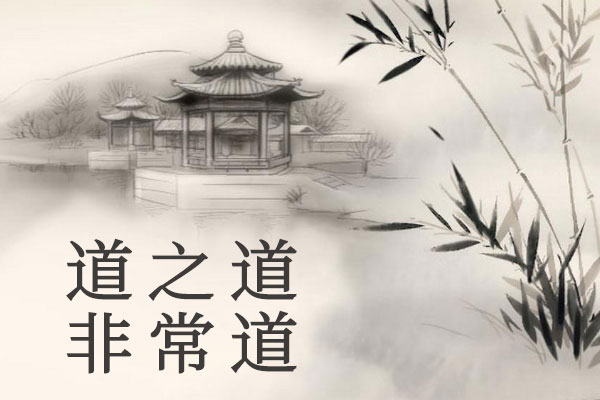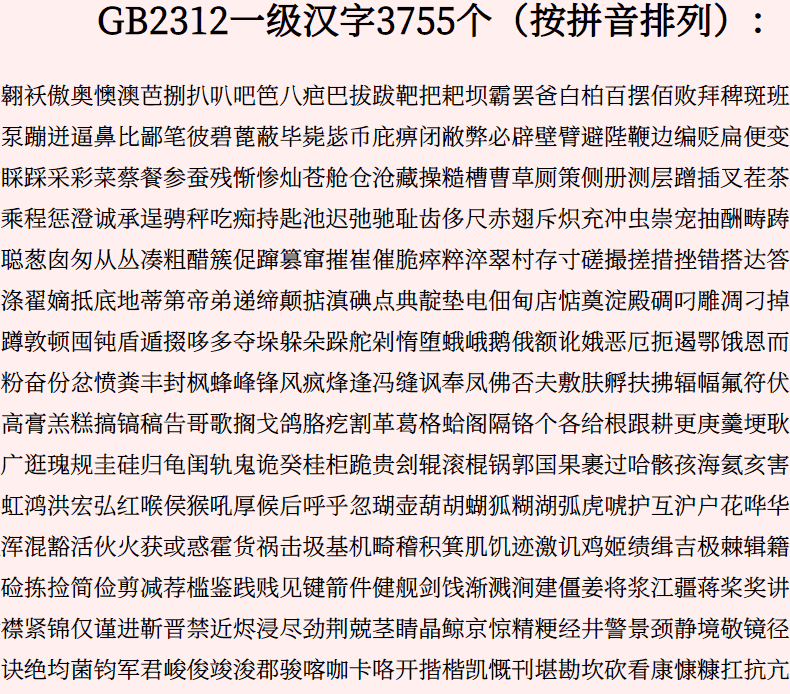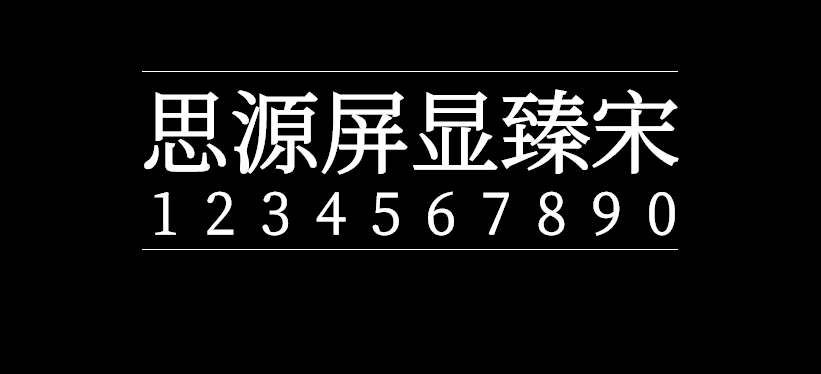
思源屏显臻宋
思源屏显臻宋(Source Han Serif CN for Display)是字体爱好者chncwk同学由于连续30天的超长假期被宅在家里,百无聊赖之际把思源屏显宋GB2312内的汉字筛选了几遍,修复了肉眼可见的笔画破损问题。另外重订了西文字母的衬线,让其回归较传统的风格,更易与汉字融合;再用极其变态的流程甄选了300多字的字形用于本项目的优化。因页面观感比起原字体有了较为明显的变化(硬朗→圆熟),故更名做全新发布,避免喜欢原风格的人被覆盖
该字体简体和繁体都支持得很好,基本没有缺字现象,大家放心下载使用!